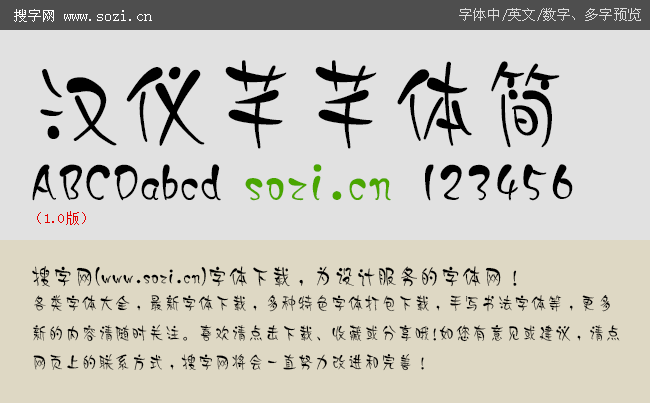
漢儀芊芊體簡1.0版
搜字網(wǎng)給大家提供一款漢儀芊芊體簡中文藝術(shù)字體下載。漢儀芊芊體是一款卡通藝術(shù)字體字形瘦長,清晰秀麗,結(jié)構(gòu)富于變化;筆畫略呈弧形,粗細(xì)變化分明或左粗右細(xì),或上粗下細(xì),粗而不黑,細(xì)而不飄;具有賞心悅目的視覺效果。適用于書籍、報刊、雜志及海報等設(shè)計使用。